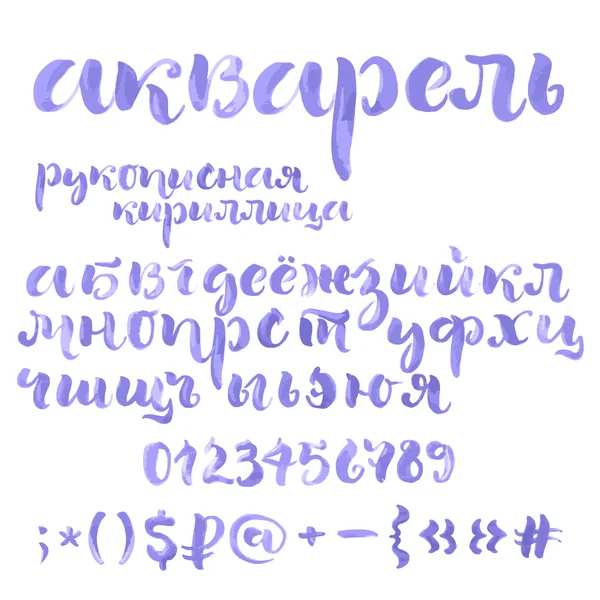
Почему брендинг салона депиляции так важен? Что стоит учитывать при выборе цветовой гаммы для фирменного стиля? Каковы особенности использования шрифтов в логотипе? Ответы здесь.
Брендинг салона депиляции – важная составляющая маркетинговой стратегии. От того, насколько привлекательным будет дизайн вашего фирменного стиля, во многом зависит восприятие бренда клиентами. Поговорим о том, как не ошибиться в выборе идеи и что стоит учесть при заказе дизайна специалисту.
Общие рекомендации по упаковке салона депиляции
Elseda советует еще до открытия сделать бренд-бук со всеми основными элементами (визитками, листовками, подарочными сертификатами, памятками клиента, оформлением вывески и зоны ресепшн и т.д.). Желательно все заказать у одного дизайнера в едином стиле с логотипом. Если есть финансовая возможность, можно сразу разработать дизайн сайта и интерьер салона в соответствии с выбранной идеей.
Цветовая гамма в брендинге салона депиляции
Большинство клиентов студий шугаринга – женщины. Поэтому при выборе цветов фирменного стиля лучше ориентироваться на их предпочтения. Прекрасно подходят нежные оттенки розового, персикового, голубого, бирюзового, фисташкового, фиолетового. Можно взять золотистый тон (особенно, если выбрано величественное название салона, например «Клеопатра»).
Если цветов в упаковке салона депиляции несколько (лучше использовать не более 3), они должны сочетаться между собой. Желательно ориентироваться на цветовой круг или таблицу сочетания оттенков. И то, и другое можно легко найти в интернете. Конечно, дизайнеры должны хорошо разбираться в этом вопросе. Однако если специалистам поступают конкретные заказы, они не всегда дают рекомендации по их улучшению.
Часто фрилансеры просто выполняют пожелания заказчика, даже если они откровенно неудачные. Поэтому лучше либо заранее определиться с желаемым результатом, либо полностью положиться на мнение профессионала и попросить его предложить несколько своих вариантов.
Беспроигрышным является сочетание любого цвета с белым. Такие комбинации смотрятся свежо и привлекательно. Если не хочется резких контрастов, можно создавать более мягкие вариации. Например, это может быть сочетание розового или бирюзового со светло-серым или персикового с приглушенно-зеленым. Черный цвет лучше вообще не использовать (за исключением логотипа). Ваша задача – создать светлый и приятный образ вашей студии.
При выборе цветовой гаммы для брендинга салона депиляции обязательно ориентируйтесь на вашу целевую аудиторию. Если в салон будет ходить преимущественно молодежь, можете выбирать яркие оттенки. Если же большая часть клиентов будет людьми среднего возраста, лучше остановиться на спокойных тонах.
Шрифты
Лучший вариант для логотипа – мягкий и несложный шрифт. Название вашего бренда должно хорошо читаться в любом размере и на любом носителе (например, на визитках или мелкой рекламной продукции вроде ручек). Учитывайте, что надпись на вывеске должна быть понятной даже издалека. Кроме того, логотип должен максимально легко вырезаться на любом материале (дереве, металле, стекле и т.д.).
Часто в погоне за красотой и изяществом владельцы салонов выбирают рукописные шрифты вроде Aquarelle. Однако они красивы лишь вблизи и в крупном формате. Стоит лишь уменьшить такой логотип, и уже будет сложно разобрать надпись. Поэтому от сложночитаемых шрифтов лучше отказаться.
Если логотип создается цветным, попросите дизайнера сделать и монохромный вариант (белый и черный). Не исключено, что вам придется использовать имя бренда в таком виде, и он должен смотреться не менее хорошо, чем в ярком цвете.
И еще один важный нюанс упаковки салона депиляции.
Логотип должен быть на русском языке. Как бы вам не хотелось выделиться оригинальной англоязычной вывеской, вы не сможете получить разрешение на ее размещение у администрации города. Обязательно использование официального языка страны, в которой будет располагаться салон.
Юридические нюансы
Обязательно запросите у дизайнера названия шрифтов, которые он использовал в логотипе. Проверьте, не платные ли они. Если шрифты платные, вы должны будете либо купить право на их использование (обычно это 100-200 долларов), либо потребовать у дизайнера заменить их на бесплатные. Использование платных шрифтов без лицензии грозит вам миллионными штрафами.